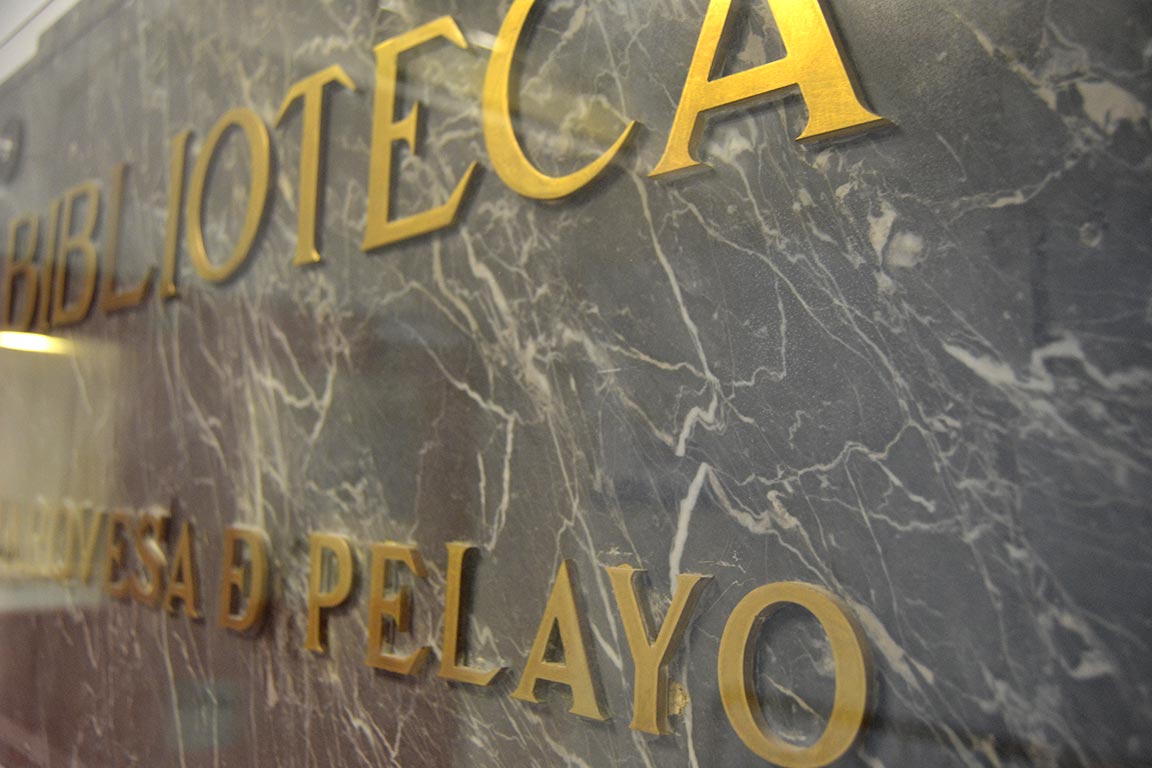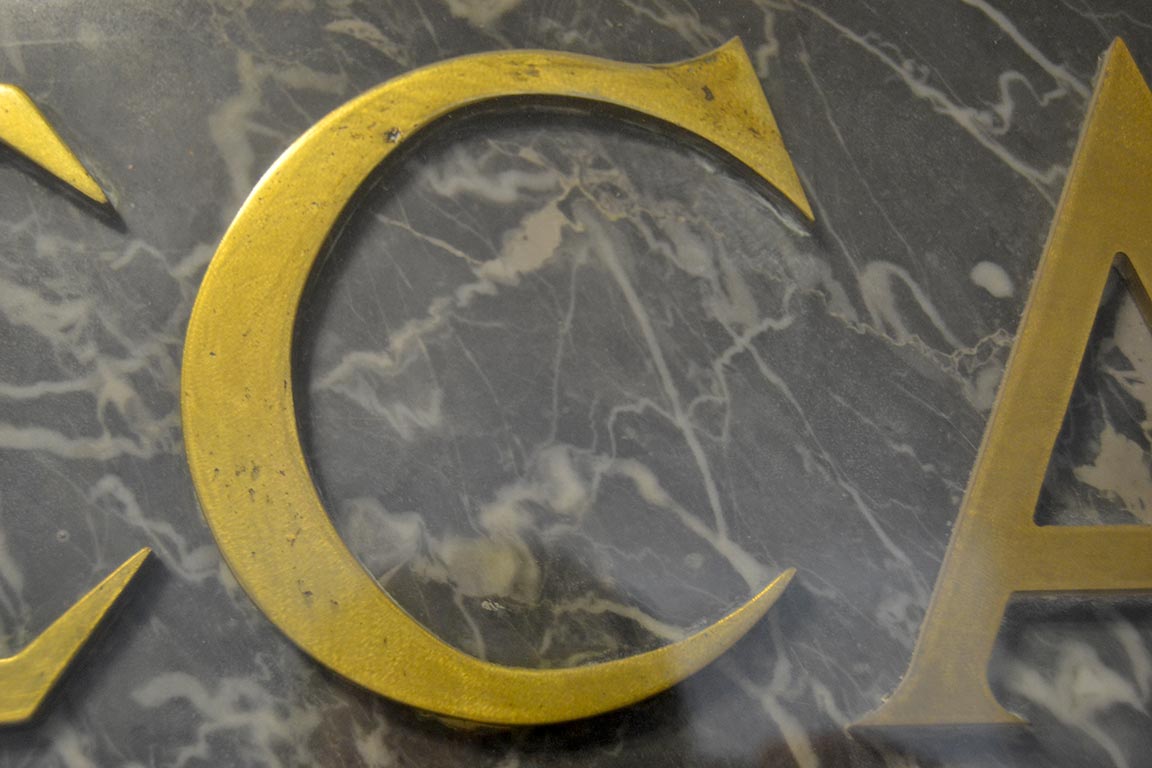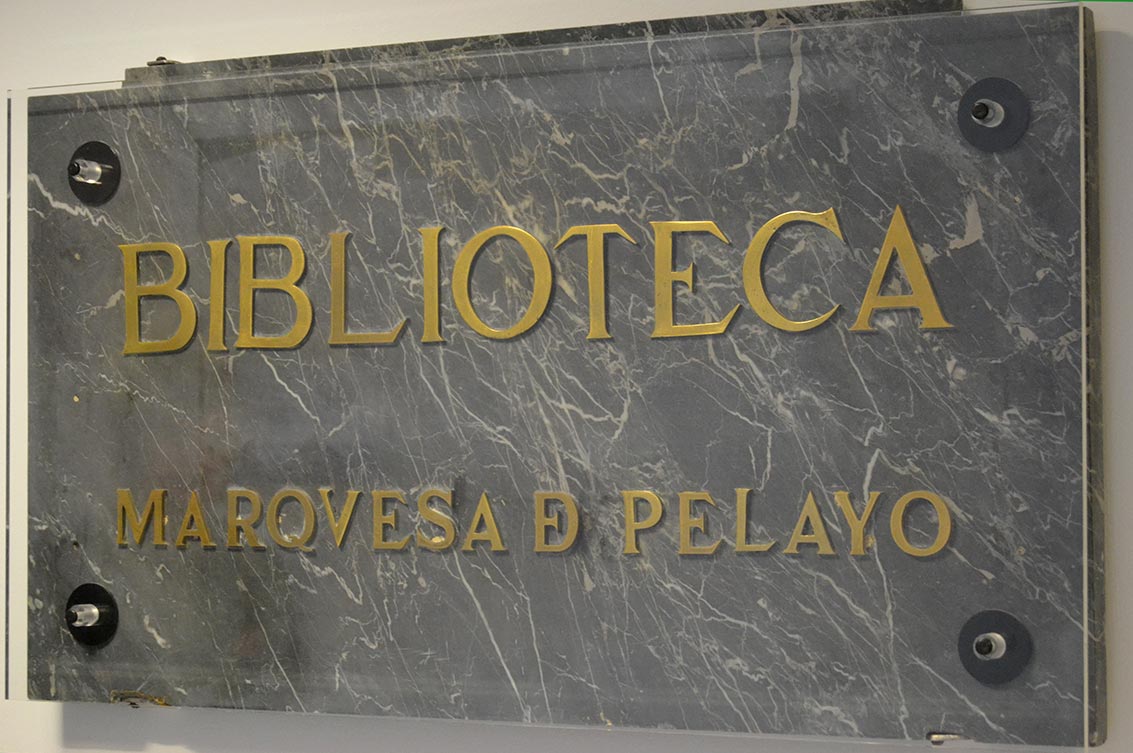
Placa de la Biblioteca del Hospital de Valdecilla
Esta placa esconde la historia de una de las bibliotecas médicas más potentes de España, y de referencia internacional desde 1929. Realizada en mármol con una tipografía clásica romana en bronce, se puede apreciar que algunas piezas han tenido que ser restauradas.
La Biblioteca Marquesa de Pelayo se inauguró a la par que la Casa de Salud Valdecilla en octubre de 1929, coincidiendo con el cumpleaños del Marqués de Valdecilla, D. Ramón Pelayo, que no pudo asistir por encontrarse enfermo. La biblioteca fue financiada por la Marquesa Maria Luisa Pelayo, sobrina del Marqués. Aunque la persona que estaba detrás de todo el proyecto era el Dr. Wenceslao López Albo, de Santander y de familia oriunda de Colindres, primer Gerente del hospital.
El Dr. Wenceslao se inspiró en la idea del Dr. Juan Madinaveitia y Ortíz, un anarquista que apuntó en la primera década del siglo XX la necesidad de crear una biblioteca médica en España, dado que aún no existía ninguna. Fue esta biblioteca médica la que estuvo como referente del conocimiento de la salud hasta el año 1985, cuando se implantó el sistema MIR, y ya a partir de entonces en cada Hospital comenzaba a contar con una biblioteca propia,  por lo que Valdecilla perdió esa centralidad  pero si perder el papel de ser la biblioteca médica más potente de España.
Como fuente patrimonial la biblioteca custodia fondos de una gran calidad y valor documental. Otra de las cosas que se conservan son parte de materiales y utensilios mueble médicos que guardan pequeñas historias de sus reputados propietarios; por otro lado hay que destacar a nivel artesanal la calidad técnica de las vidrieras de la Sala Noble, sala que generalmente se usa en las reuniones. Entre algunos de los detalles que se pueden ver en dichas vidrieras, está lo que puede ser una representación del escudo más antiguo que se conoce de Torrelavega.
Recientemente ha salido a la luz un material documental importante: Cajas de archivos con todas las Facturas de gasto de la antigua Casa de Salud. Este tipo de documentación nos pueden aportar datos económicos y conocer que tipo productos se consumían tanto de alimentación como de logística; por otro lado nos puede aportar datos sociales sobre el comercio local de la Región, como proveedores de la Casa de Salud.
En esta imagen se puede ver la ubicación de la placa en la sala. © Foto de Pablo Hojas (Padre). Foto cedida por la Biblioteca Marquesa de Pelayo.
Actualización 2019:
Recientemente se ha incorporado a la colección de Santatipo una jarrita original donada para el proyecto de la antigua Casa de Salud de Valdecilla, circa años 30-40. En la misma se puede ver el viejo logo,  y en su base los datos de fabricación, así como el teléfono y sello de la antigua Ibero Tanagra, la fábrica más importante de loza de Santander. La denominación de «Casa de Salud de Valdecilla» permanecería activa hasta 1972 cuando pasa a denominarse como lo conocemos hoy: Hospital de Valdecilla.